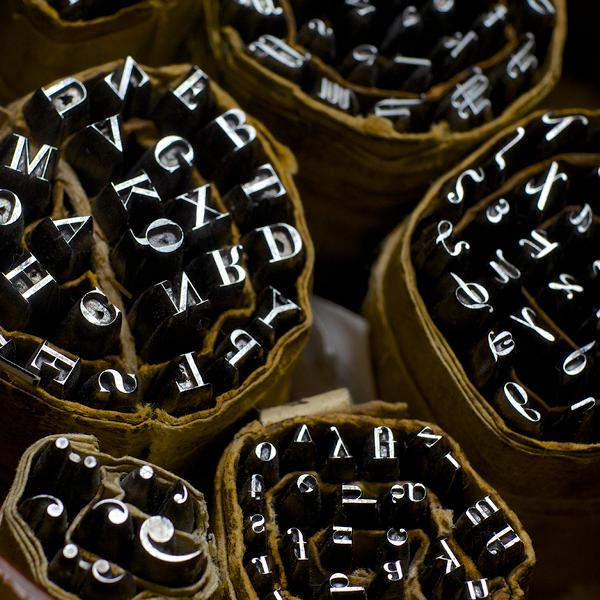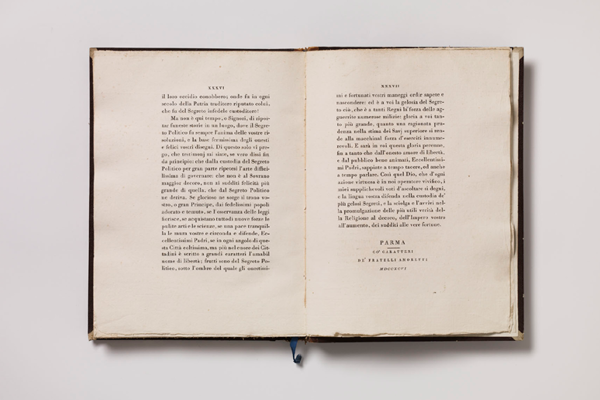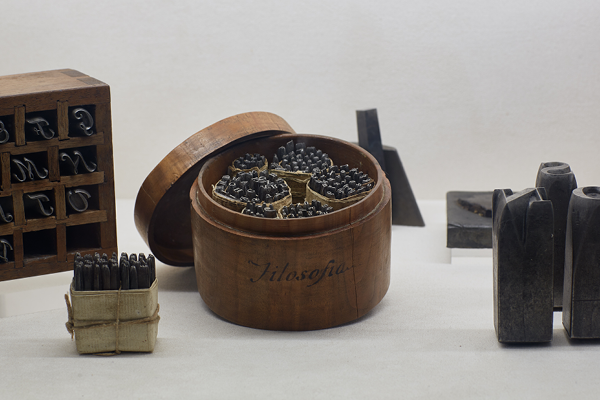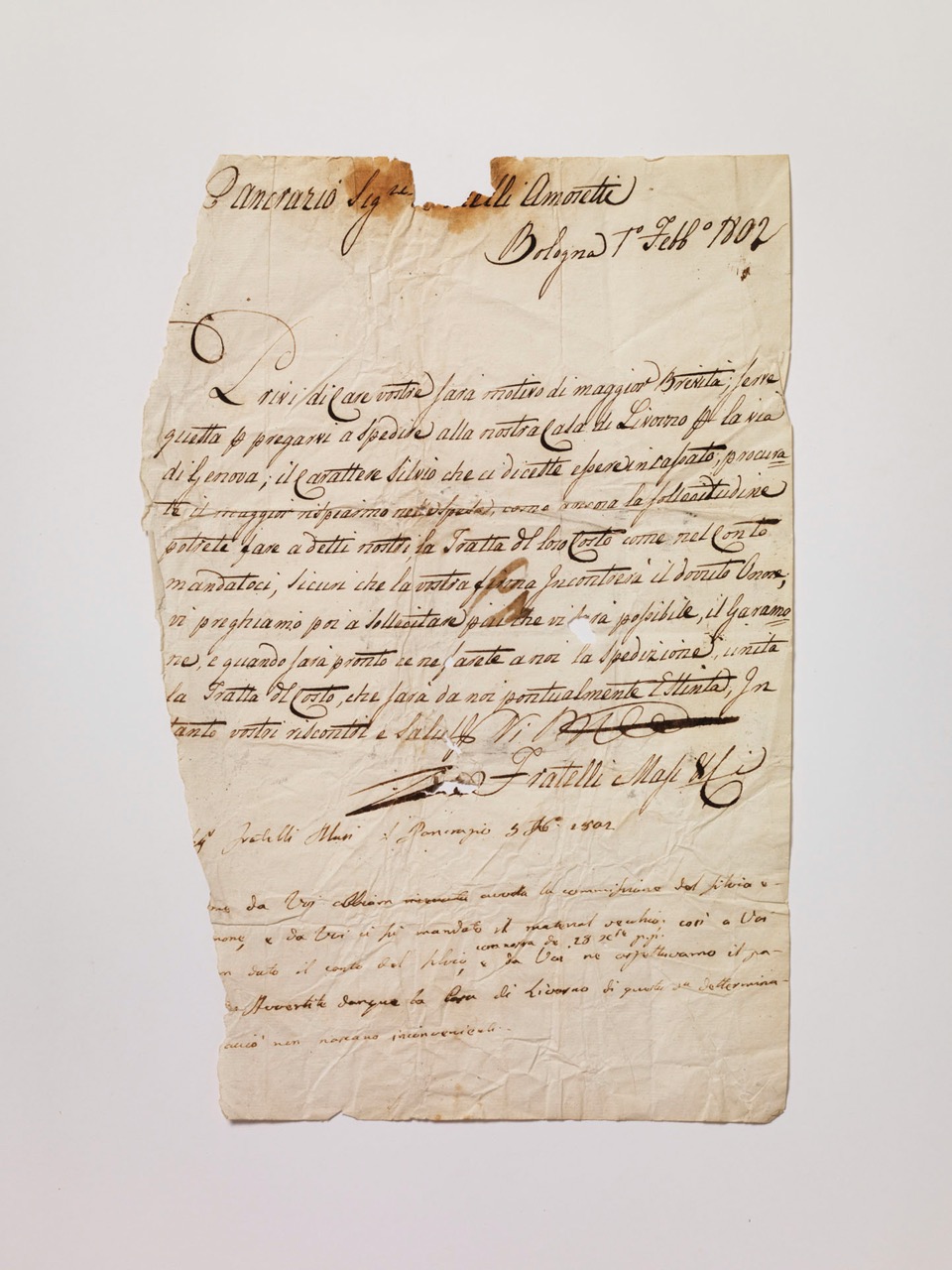
Fonderia Fratelli Amoretti
Le vicende della famiglia Amoretti, originaria di San Pancrazio (sobborgo alla periferia occidentale di Parma), si legano a quelle di Bodoni e del suo operato come produttore di caratteri. È molto probabile che Giambattista Bodoni, ingaggiato dal ministro Guillaume Du Tillot nel 1768 per realizzare a Parma una Stamperia Reale, decise di allestire l’officina con torchi e strumentazione nuovi, rivolgendosi innanzitutto a maestranze locali. Come riferito con più precisione da diverse fonti di inizio ’800, Bodoni cominciò ad avere pratica con gli Amoretti – già famosi per il loro lavoro di fabbri – nel 1774, con l’occasione di ordinare loro nuove forme in acciaio per il gettito di diversi caratteri. Agli Amoretti si deve infatti l’incisione dei punzoni per alcune delle serie che prenderanno il nome del tipografo di Saluzzo, diventando tra i caratteri più famosi e utilizzati.